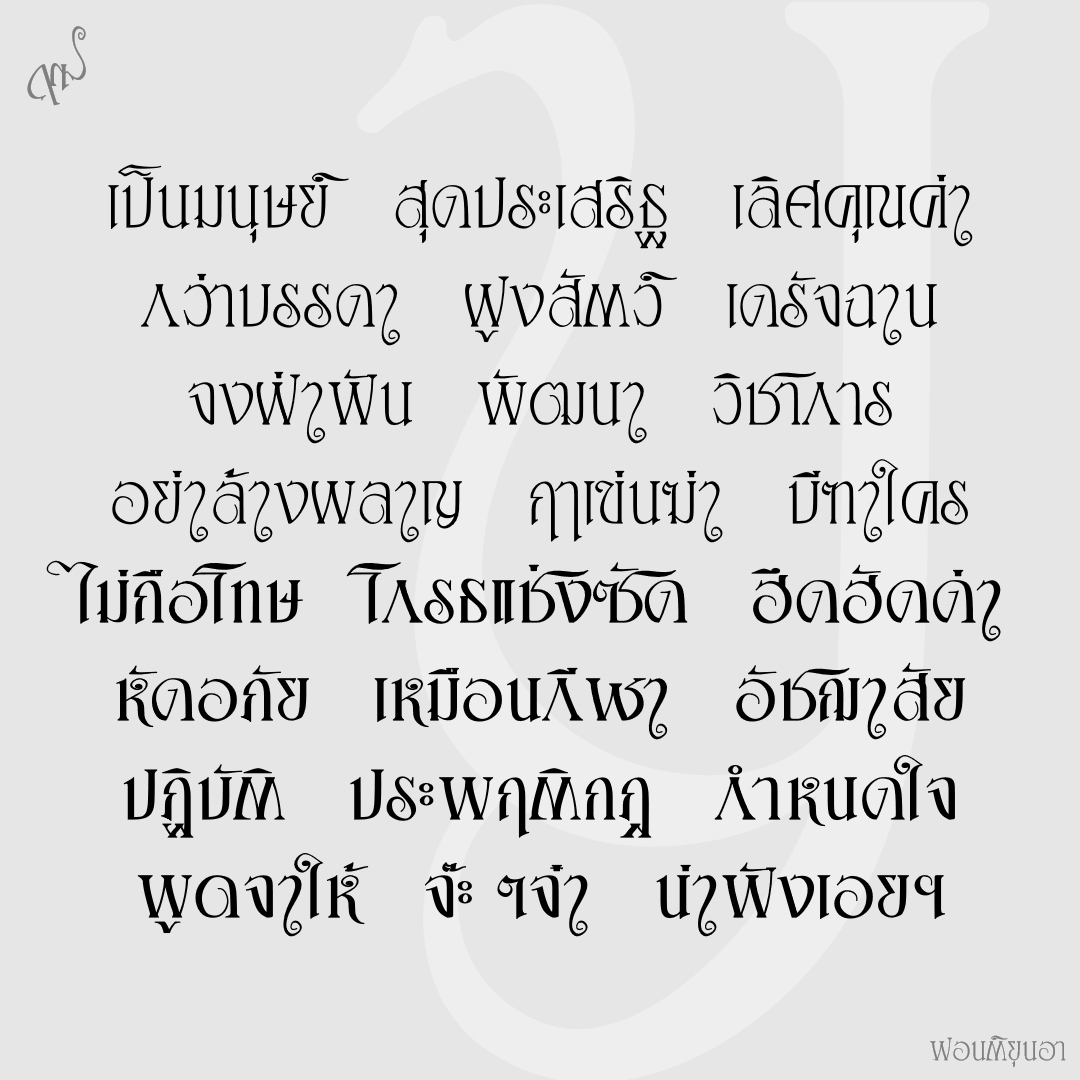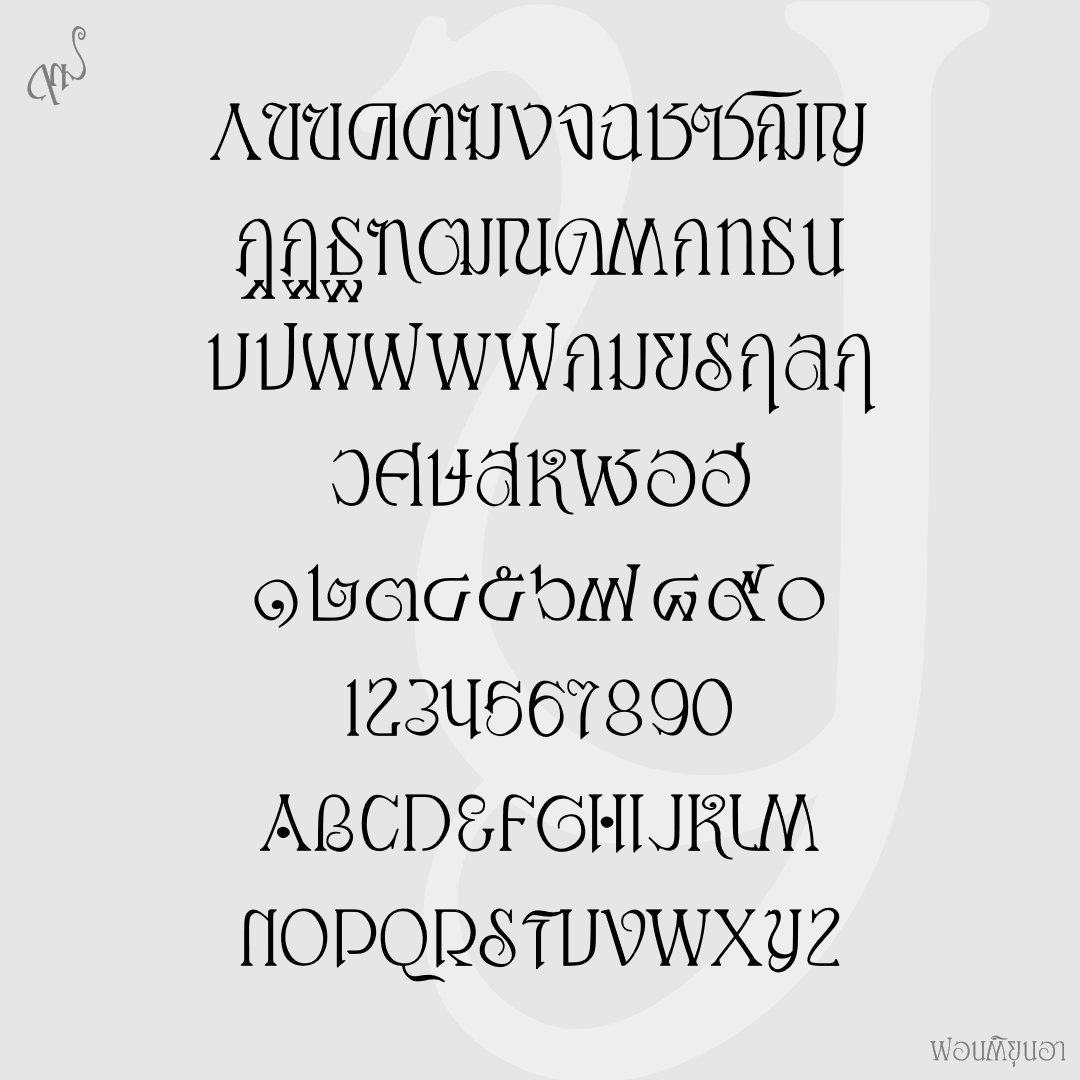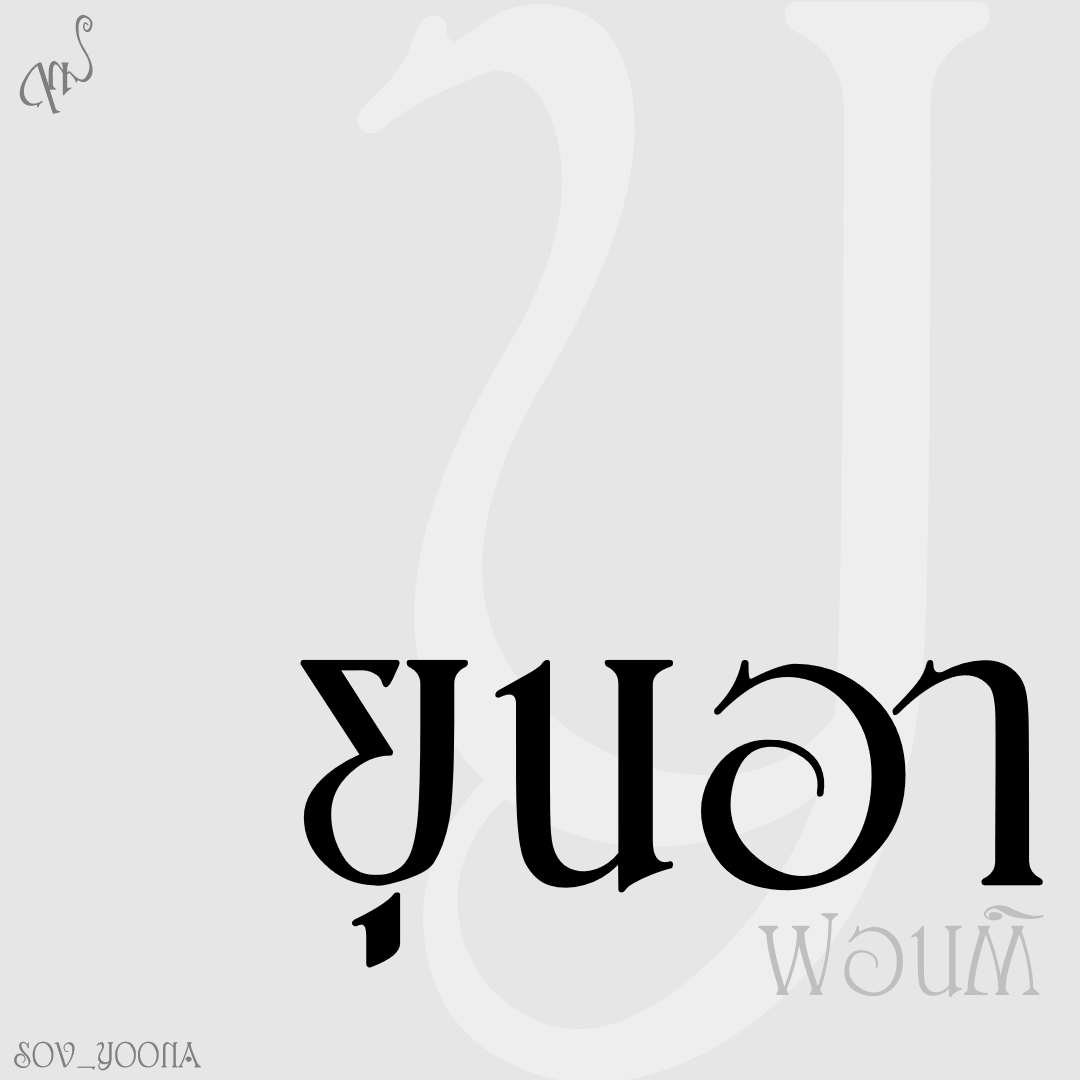
ฟอนต์ ยุนอา
ฟอนต์ยุนอา ต้นทางจากโปสเตอร์หนังเรื่อง "มนต์รักอสูร" และ "ไฟรักอสูร"
ชื่อฟอนต์ : ยุนอา
ฟอนต์ยุนอา ต้นทางจากโปสเตอร์หนังเรื่อง "มนต์รักอสูร" และ "ไฟรักอสูร"